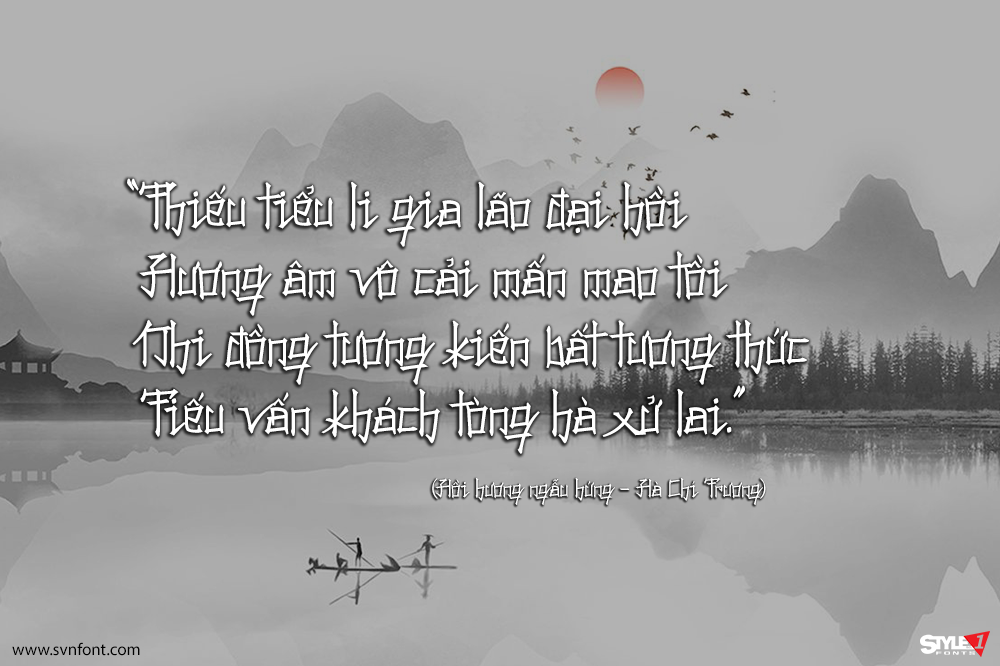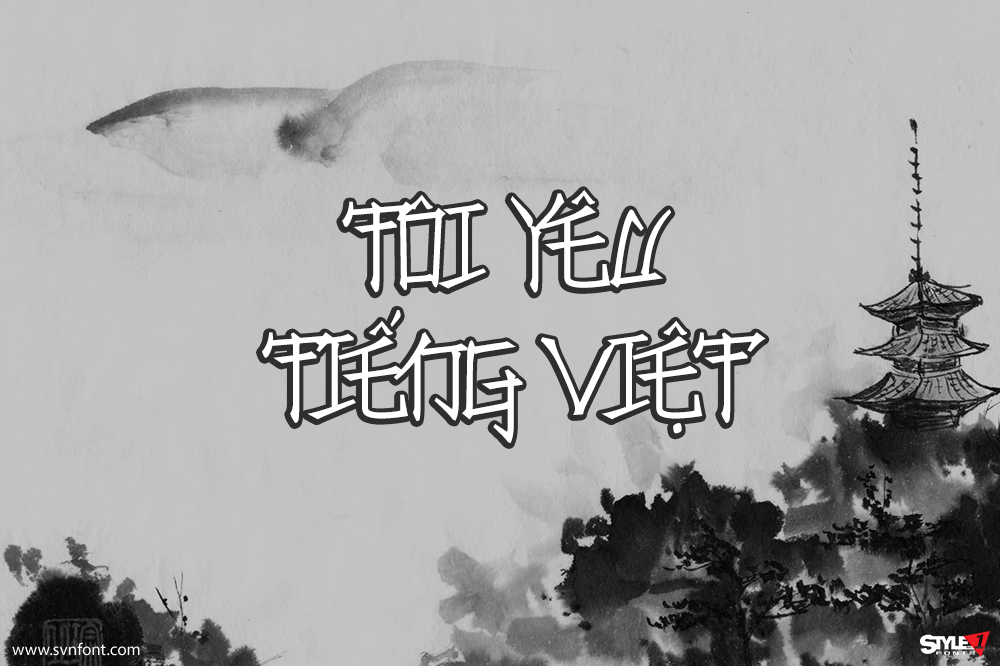
Konfuciuz là typeface phong cách Trung Hoa đến từ Apostrophic Labs. Font là lựa chọn thích hợp cho tiết kế về văn hóa, du lịch, ẩm thực… các nước Á Đông như Trung, Nhật, Hàn…
Nhà thiết kế: Apostrophic Labs
Nhà phát hành: Apostrophic Labs